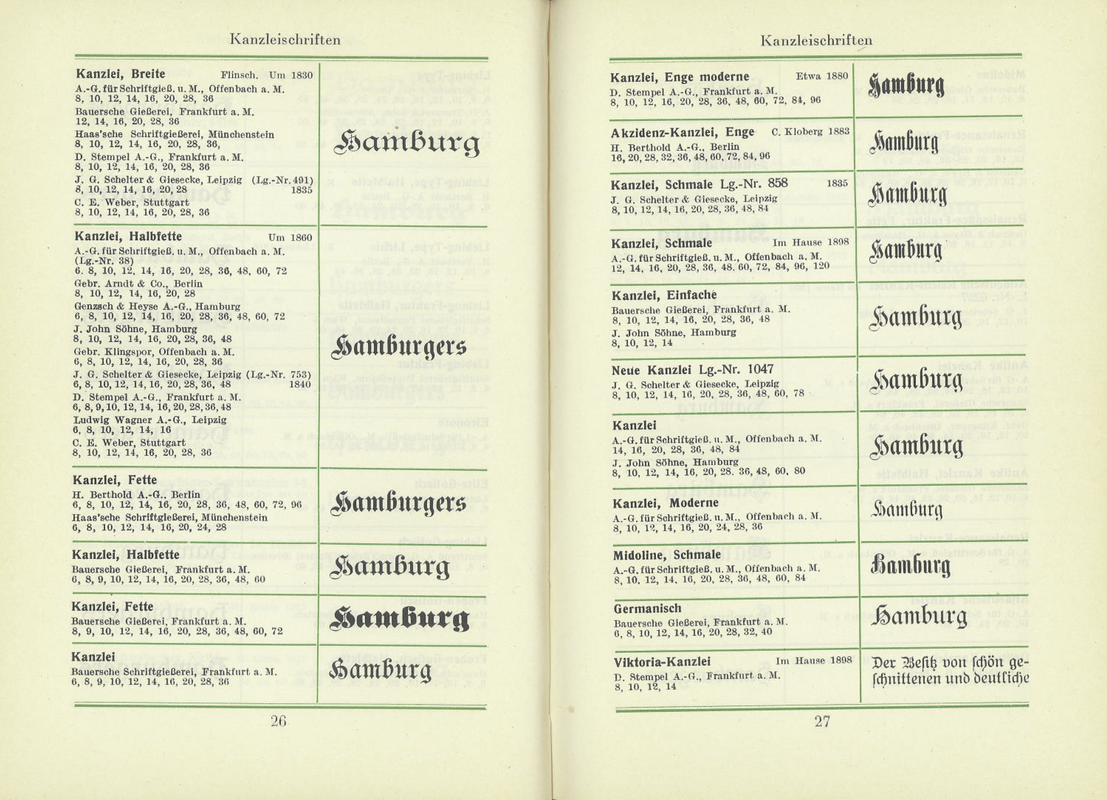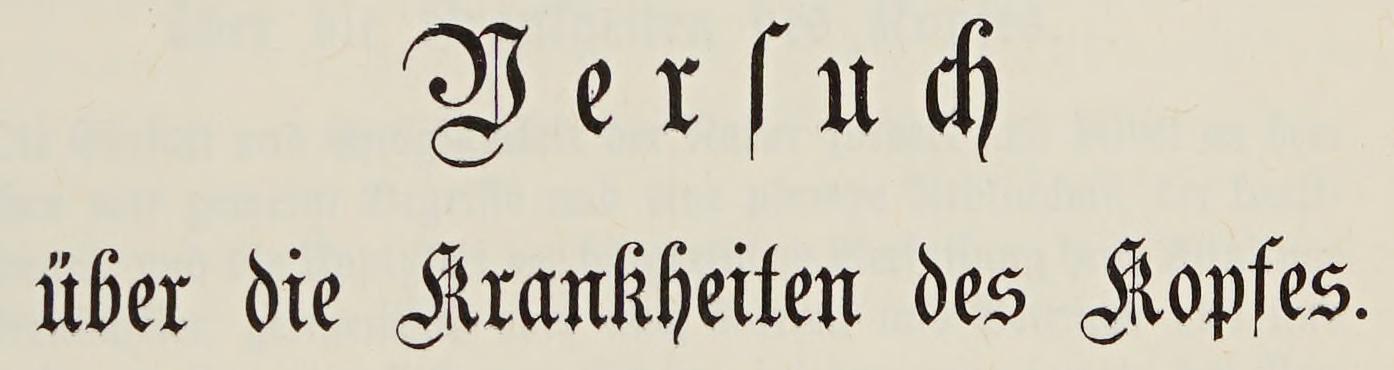
Titelfraktur gesucht (Kant’sche Gesamtausgabe)
in der Kant’schen Gesamtausgabe mit den Vorkritischen Schriften, die von der „Deutsche Akademie der Wissenschaften zu Berlin“ ca. 1912 herausgegeben wurde, habe ich eine schöne Titelschrift gesehen, die ich aber leider nicht identifizieren konnte. Kennt vielleicht jemand von euch diese Titelfraktur?
Das Design lief unter dem generischen Namen Kanzlei und war in vielen verschiedenen Varianten von verschiedenen Herstellern erhältlich.
Im Seemann schauend, scheint die Variante Einfache Kanzlei von Bauer recht gut zu passen. Die gäbe es bei Helzel auch digital.